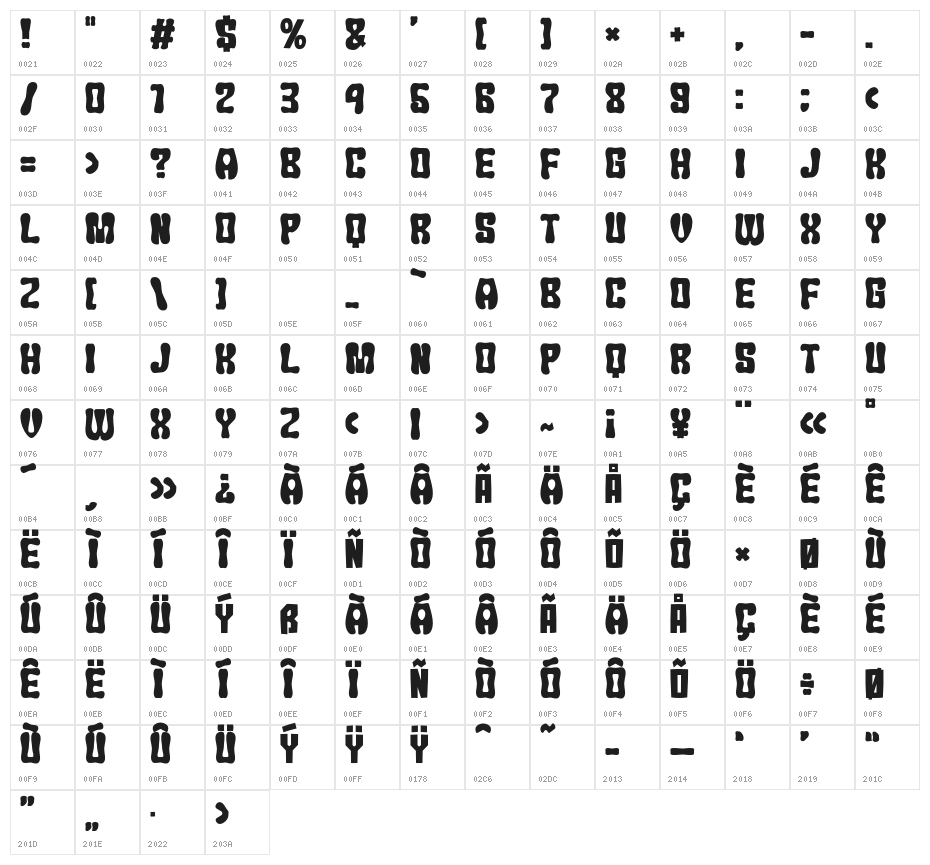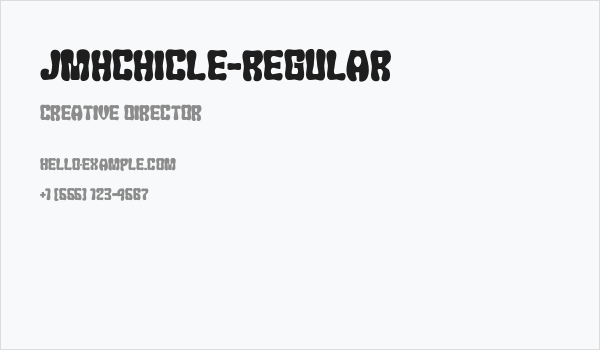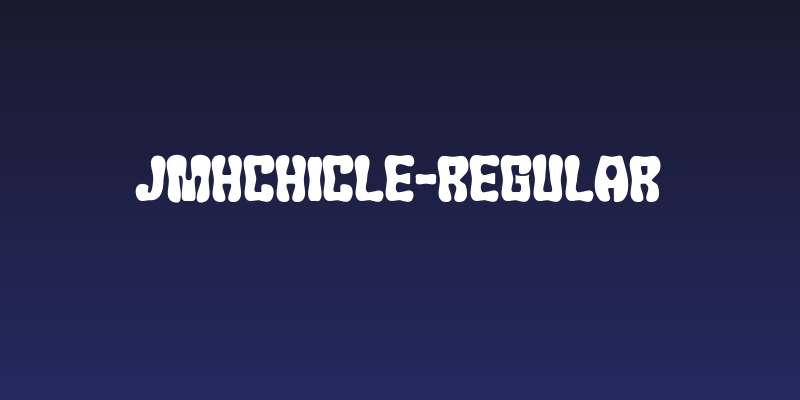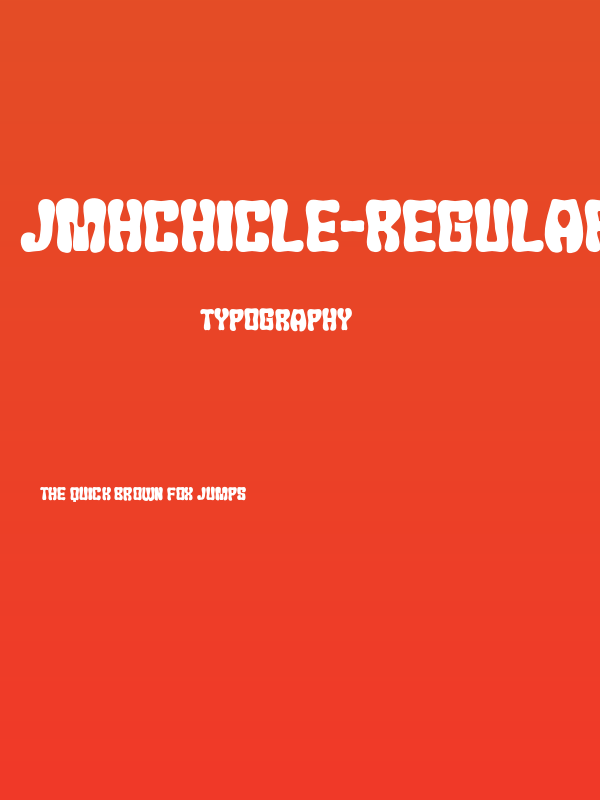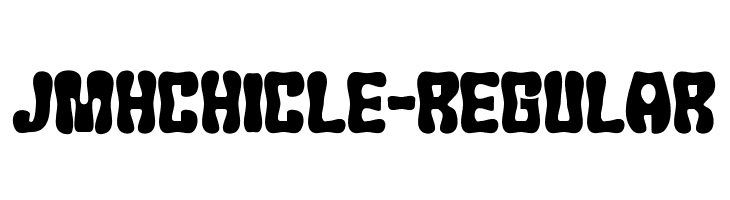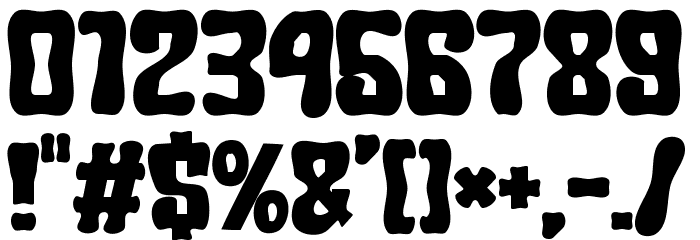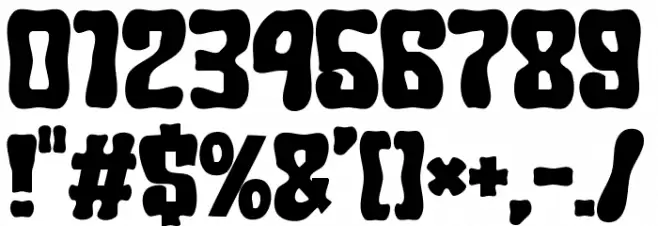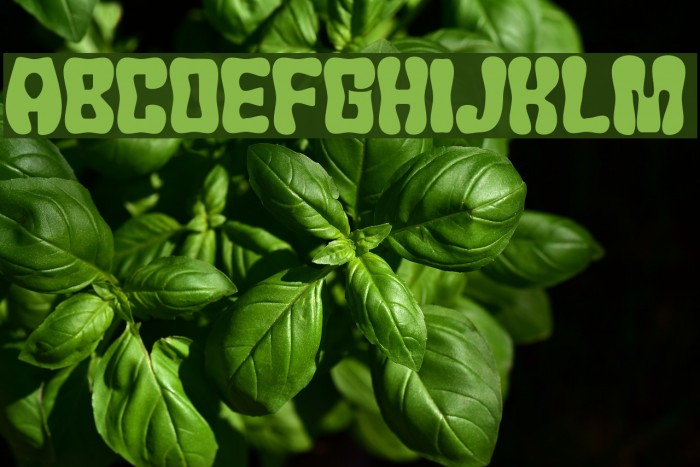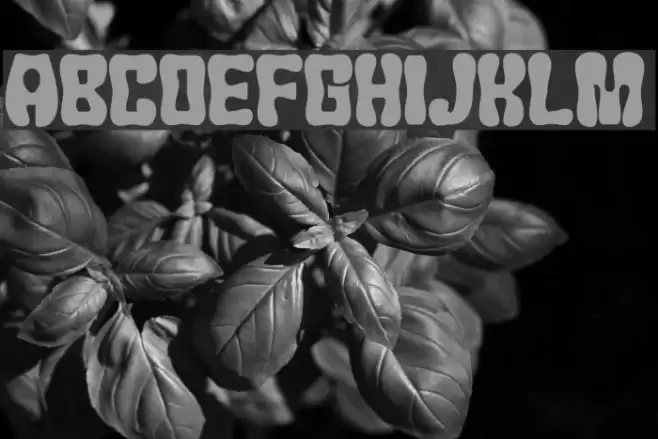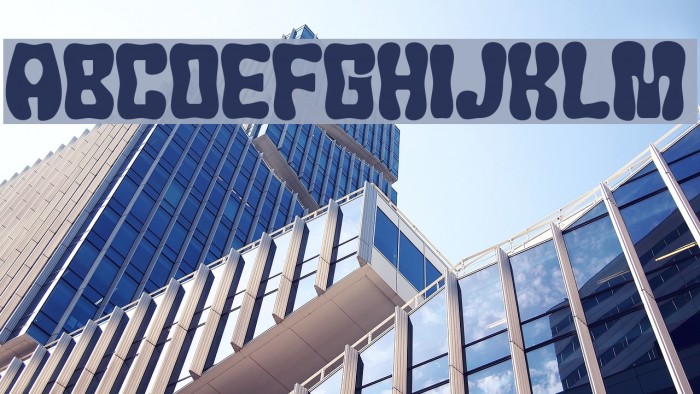
JMHChicle-Regular Font
| Stil general | Playful, Cartoonish |
| Proiecte propuse | Ideal for children's books, comic strips, playful branding, and party invitations. |